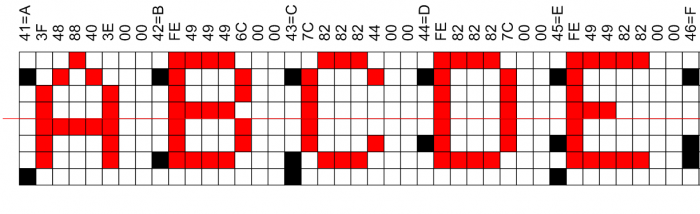
Für ein Projekt suche ich eine Bitmap Font. Es ist ein technisches Display, deshalb muss es pixelbasierend sein.
Ich habe schon viel gesucht, aber die Höhe passt meist nicht.
Fällt Euch vielleicht etwas dazu ein?
- Pixelmaß Höhe 11-13 px / Breite 7-9 px
- Da Schrifteinfärbungen, ohne Anti-Alias-Pixel mit sogenannten 01-Pixeln
- Linienstärke gerne 2px wegen Lesbarkeit und Kontrast
Software zum Umwandeln herkömmlicher Schrift habe ich schon getest, funktioniert aber auf der  kleinen Größen nicht.
Ich dachte schon ans selber bauen oder anpassen.
Versuchs doch mal mit »fontstruct« … Bei Pixelschriften mit deinen Vorgaben könntest du unter Umständen mit den zehn Prozent Schwierigkeiten bekommen, aber bei Pixeln lässt sich der Anteil zumindest sauber berechnen ;-)  (wo hast du das eigentlich her, mon dieu)  PS: selber bauen klingt gut! Nur Mut! PPS: ich hoffe es ist klar geworden, das es sich dabei auch um einen editor handelt, mit dem es möglich ist Pixelfonts zu erstellen
Hier würde ich zunächst die technische Dokumentation des Herstellers dieses Displays genau betrachten, um die genauen Anforderungen der Schrift  und wie diese dann repräsentiert sein muss, in Erfahrung zu bringen. Oft können solche Displays nichts mit Computerfonts anfangen, und brauchen ein speziell programmiertes Zeichensatz-E-PROM.
Meine allererste digitale Schrift war so ein Fall, eine Schrift für ein digitales Meßinstrument, dass statt unbenötigter Schriftzeichen im US-Zeichensatz-ROM dann deutsche Umlaute enthalten sollte.
Wenn ich das noch richtig zusammen bringe war das so:
Im ROM nur eine reihe von Bytes, jeweils 8 Byte pro Zeichen, das erste Bype ist der ANSI Zeichencode , gefolgt von 5 Bytes für die Spalten des Buchstaben, gefolgt von 2 mal 0 als „Nachbreite“ etwa wie in dieser Skizze:
So wie es aussieht wurde jetzt doch die Möglichkeit gefunden, eine Antialiased Schrift zu verwenden.
Das würde das ganze vereinfachen.
@Hans
Inzwischen habe ich noch weiter recherchiert.
Schriftzeichen sind nicht so sehr geschützt, wie beispielsweise Logos.
Man unterscheidet auch zwischen "Brotschriften" also die zum täglichen gebrauch und Zierschriften, die sich besser schützn lassen.
Bitmap Schriften stellen aber kein rechtlich gesehenes "Kunstwerk" dar und sind dann Brotschriften.
Generell 10% sind nicht ausschlaggebend , wichtig ist, dass ein neuer Gesamteindruck entsteht, um die Schrift durch Geschmacksmuster schützen zu lassen.
Das ist natürlich immer schwierig zu entscheiden. Aber z.B. wollte Microsoft die Segoe UI schützen lassen, das wurde vor Gericht zurückgewiesen, weil sie zu nah an der Frutiger dran war...
Ich habe hier eine gute Zusammenfassung  gefunden über den rechtlichen Schutz von Schiften.